‘한글폰트 저작권 보호’에 대한 산돌의 생각
폰트의 디자인을 창작된 저작물로 인정하고, 디자인보호법이 아닌 저작권법으로 보호하는 제도적 보완은 오랜 시간이 필요할 것입니다. 하지만 더 이상 한글 폰트는 아예 저작권이 없다는 오해는 사라져야겠습니다. 폰트 파일 없이 폰트의 디자인만 사용했다는 억지도 더 이상 없어야겠습니다. 한글 폰트에 대한 창작을 인정해 줄 때 폰트 디자이너들이 더 좋은 한글 폰트를 만들어내려는 노력이 커질 것이고, 외국 기업들의 한글 폰트 표절도 예방할 수 있을 것입니다.
한글 폰트가 당면한 현실
‘한글은 세종대왕 시절에 발명된 것이니 세종대왕이 저작권을 가져야 한다’
한글 폰트에 대한 저작물로써의 권리를 토론할 때 자주 나오는 의견입니다. 현대의 저작권 제도를 바탕으로 세종대왕이 한글을 발명한 특허권과 저작권을 주장한다면 당연히 인정될 것도 같습니다. 만약 그랬다면 우리는 엄청난 저작권료를 지불하면서 한글을 사용하고 있거나, 지금도 한자를 사용하고 있었을 것입니다. 다행하게도 세종대왕은 한글을 자신의 것으로 하지 않고 백성을 위해 오픈 라이선스로 공개했기 때문에 한글을 마음껏 사용할 권리와 지키고 발전시킬 책임까지 우리 민족과 만백성이 골고루 나누고 있습니다.
‘알파벳으로 쓰면 디자인이 살고, 한글로 쓰면 디자인이 죽는다’
현업의 디자이너들이 자주하는 하소연입니다. 이 얘기는 ‘한글’이 디자인에 어울리지 않는 것이 아니라, 디자인에 어울리는 ‘한글 폰트’가 부족하다는 것이 정확한 표현일 겁니다. 우리가 한글을 더 잘 사용하기 위해서 더 좋은 한글 폰트가, 더 다양하게, 더 많이 만들어져야 한다는 점에는 아무도 이견을 꺼낼 수 없습니다만 실제 한글 폰트를 만드는 사람들은 지금 어떤 환경에 처해 있을까요?
한글은 반포된 지 600년에 가까워지고 있습니다. 하지만 한글이 체계적으로 쓰이기 시작한 것은 100여년에 불과하고, 한글 폰트가 만들어지기 시작한 것은 겨우 30여년 밖에 되지 않습니다. 한글 폰트를 제작하는 회사는 30여개로 늘어났지만, 경쟁력을 갖춘 역량 있는 한글 폰트 디자이너는 전세계를 통틀어 100명도 되지 않습니다. 초중고에서는 타이포그래피에 대한 교육을 전혀 하지 않고, 대학에서도 디자인 전공자에게 한 학기 정도의 교육을 할 뿐, 체계적으로 한글 폰트 디자인을 다루는 교육 기관도 아직은 찾아보기 어렵습니다. 간혹 열정을 가지고 폰트 디자이너가 되길 희망하는 사람들이 있긴 하지만, 그들이 일할 수 있는 곳도 거의 없습니다. 당연히 한글 폰트를 만드는 사람들은 점점 줄어들고 있고, 한글 폰트를 만들던 사람들도 다른 직종으로 전업을 하는 사례가 늘고 있습니다.
왜 그렇죠? 폰트 회사들이 저작권료로 많은 돈을 번다는데
초성, 중성, 종성이 조합을 통해 조형을 구성하는 한글은 획의 작은 변화에 따라 가독성, 심미성, 사용성이 크게 달라지기 때문에 알파벳보다 만들기가 훨씬 어렵습니다. 게다가 기호까지 포함된 알파벳이 100여자 정도인 것에 비해, 한글은 11,172자로 만들어지기 때문에 개발에 필요한 절대 시간이 훨씬 오래 걸리게 됩니다. 그렇게 한자씩 만들어진 11,172개의 글자가 서로 잘 어울리는지를 확인해야 하는 경우의 수를 생각하면 한글 폰트 1종을 개발하는 것이 얼마나 많은 시간과 노력이 필요한지 가늠할 수 있을 것입니다. 그렇게 디자이너 한 사람이 1년에 만들 수 있는 한글 폰트는 기껏해야 2~3종이고, 한글 폰트를 ‘제대로’ 개발하는데 들어가는 비용은 1종에 최소한 3~5천만원 정도가 필요합니다.
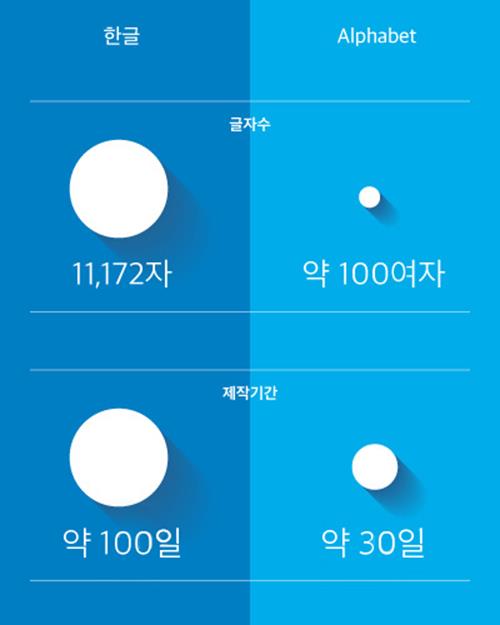
한글 폰트를 만드는데 이렇게 많은 비용이 필요하다 보니, 많은 수의 소규모 한글 폰트 업체들은 좋은 한글 폰트를 만드는 능력을 키우기보다는 쉽게 빨리 만들어서 모바일 플랫폼에 판매함으로써 생계를 유지하고 있습니다. 심지어 몇몇 업체에서는 유명한 폰트나 디자인 작품을 표절해서 한글 폰트를 만들기도 하고, 이렇게 표절한 폰트들이 방송과 광고 등에 부끄럼 없이 사용되는 일도 자주 벌어지고 있습니다. 안타까운 현실이지만 이들에게는 생계가 달려 있는 문제이기 때문에 무조건 탓할 수도 없습니다.
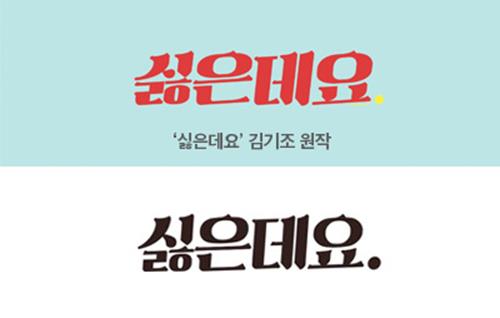
그리고 많은 분들이 가장 크게 오해하고 있는 부분이 한글 폰트 회사들이 저작권 단속을 통해 많은 돈을 벌고 있다고 생각하는 것입니다. 우리나라에서 가장 큰 한글 폰트 회사인 산돌과 윤디자인, 두 회사의 1년 매출을 합해도 80억원 정도에 불과하고 순수익은 별로 없는 것이 현실입니다. 규모가 작은 회사들은 더욱 심각한 상황입니다. 한글 폰트 디자이너들이 좋은 폰트를 만들기 위해 많은 야근을 하면서도 박봉에 시달리는 이유가 달리 있지 않습니다. 우리나라에서 한글 폰트 회사들은 많은 돈을 벌기는 고사하고, 늘 생존의 위협을 받고 있습니다. 폰트 업계가 저작권 단속에 매달리는 이유가 여기에 있습니다.
한글 폰트 저작권 단속의 실체
한글 폰트 업체들의 폰트 저작권 단속이 비난 받는 이유는 ‘함정 단속’ 때문입니다. ‘개인적 용도에는 무료’라고 배포해 놓고, 라이선스 범위에 대해서는 모호하게 감춘 다음 함정에 걸리면 ‘상업적인 용도’에 사용했다면서 단속을 해서 비싼 합의금을 요구하는 방식입니다. 이런 방법이 효과를 거두자 더 대담하게 네이버 등의 포털 서비스를 통해서 무료 폰트라며 대량 배포해서 더 많은 피해자를 양산하는 사태에 이르고 있습니다. 이 회사들이 함정 단속을 하는 이유는 이들의 폰트를 돈을 내고 구매하는 사람이 없기 때문에, 단속을 마치 영업 활동처럼 여기기 때문입니다. 값을 지불하기에는 폰트 품질이 부족하다는 것이 가장 중요한 이유겠지만, 그만큼 폰트를 제 값 주고 구매하는 사람이 별로 없다는 것도 사실입니다. 앞으로도 이 회사들의 한글 폰트를 사용할 생각이라면 무료 폰트라는 말에 속지 말고, 라이선스에 대해서 정확히 확인한 후에 사용하는 것 밖에는 방법이 없습니다. 함정이라는 것을 정확히 알고, 함정을 피해야 합니다.
한글 폰트는 그냥 써도 저작권 침해가 아니라는데요
‘폰트는 저작권이 없다, 그러니까 그냥 써도 된다’
이 이야기가 마치 사실인 것처럼 통용되고 있습니다. 이런 큰 오해가 발생하게 된 것은 정부와 기관의 탓이 크지만, 단속에만 열을 올리고 고객들과 소통에는 소홀했던 한글 폰트 업체들에게도 책임이 있습니다. 너무도 당연한 이야기지만 폰트도 저작권법 상의 프로그램 저작물로 보호되고 있습니다. 따라서 저작권자의 허락 없이 폰트를 사용하게 되면 저작권 침해에 해당합니다.
그러면 왜 폰트는 저작권이 없다는 얘기가 나온 것일까요? 한글 폰트에 대해 저작물로 인정되지 않는 부분이 한가지 있는데 그것이 한글 폰트의 도안 즉 ‘디자인’ 입니다. 폰트의 핵심이 서로 다른 폰트임을 구분할 수 있는 ‘디자인’ 임에도 불구하고, 저작권 법에서는 고딕체와 명조체를 서로 같은 디자인이라고 판단하고 있는 것입니다. 여러분이 생각하기에도 고딕체와 명조체는 같은 것으로 생각되시나요?
한글 폰트의 디자인을 저작물로 인정하지 않는 이유는, 모든 한글 폰트가 세종대왕 시절에 고안된 한글을 똑같이 그리고 있는 것 뿐이기 때문에 새로운 창작물로 볼 수 없다는 것입니다. 김수현을 사진으로 찍으면 그 사진들은 모두 각각의 저작물로써 촬영자에게 저작권이 발생하게 되고, 김수현은 별도의 초상권을 행사하게 됩니다. 그런데 한글 폰트는 오랜 시간을 들여서 디자이너의 창작 활동을 통해 각기 다른 모양으로 그려내도 저작물로 인정해주지 않는다는 것이 현재 한글 폰트에 대한 제도적 인식입니다. 왜 김수현의 똑같은 모습을 찍은 사진에는 저작권을 인정해주고, 한글은 인정해주지 않는 걸까요?
폰트의 디자인을 저작물로 인정하지 않는 저작권법의 해석 때문에 ‘폰트는 저작권이 없다’라는 큰 오해가 발생한 것입니다. 심지어 똑같은 폰트의 디자인을 복사해서 새로운 폰트라고 이름 붙여도 법률상으로는 아무런 문제가 없습니다. 어도비나 모노타입과 같은 거대 기업이 한국에 있는 모든 한글 폰트를 그대로 표절해서 새로 이름을 붙이고, 자기들의 폰트라고 주장해도 우리나라의 저작권법으로는 대응할 방법이 없습니다.
‘폰트 디자인도 디자인보호법으로 보호됩니다’
저작권법이 폰트의 디자인은 저작물로 보호하지 않으니까 폰트 디자인은 마음대로 베껴서 사용해도 된다고 생각할 수 있습니다. 실제로 폰트 저작권 단속에 걸린 사람들이 주장하는 것이 ‘폰트 파일을 사용하지 않았고, 폰트 디자인만 따서 사용했다’라는 것입니다. 하지만 폰트의 디자인만 도용한 것도 처벌받을 수 있다는 사실은 제대로 알려지지 않았습니다.
저작권법은 폰트 파일만 보호하고 폰트 디자인은 보호하지 않지만, 별도의 법률인 디자인보호법에서는 폰트의 디자인까지 온전히 보호하고 있습니다. 그러니까 폰트의 디자인은 저작권 침해가 아니라고 생각해서 무심코 사용했다가 디자인 등록이 돼 있는 폰트라면 디자인보호법 위반으로 처벌될 수 있습니다.
● 폰트는 저작권법 상에 프로그램 저작물로 보호됨
→ 따라서 저작권자의 허락 없이 폰트 파일을 이용하거나 복제, 전송하는 것은 저작권 침해
● 폰트 디자인은 디자인보호법으로 보호됨
→ 따라서 폰트 파일을 사용하지 않았더라도, 디자인 등록된 폰트의 디자인을 도용하면 디자인보호법 위반
디자인보호법이 있다면 굳이 폰트 디자인에 대해 저작권을 인정해달라고 할 필요가 없지 않느냐는 얘기도 많이 듣습니다. 반대로 디자인보호법에서 폰트 디자인 보호하고 있다는 것은 폰트 디자인을 보호할 필요성을 제도적으로도 이미 인정하고 있다는 의미인데, 저작권법에 포함하면 간단할 일을 별도의 등록 절차와 비용이 필요하고, 국제적으로는 인정되지 않는 디자인보호법에서 다루는 것은 행정력과 비용 낭비일 것입니다.
‘폰트의 글자 디자인은 사용했는데, 폰트 파일은 쓰지 않았다구요?’
폰트를 사용한 결과물은 있는데, 폰트 저작권을 침해하지 않았다는 주장은 ‘폰트를 사용하지 않고 똑같은 글자 모양을 만들어냈다’는 얘기가 됩니다. 정말 폰트 파일을 사용하지 않고도 그런 작업을 할 수 있을까요? 밥은 먹었는데 쌀은 먹지 않았다고 주장할 수 있을까요?
이런 행위를 합리화시키기 위해서 ‘한글 폰트에는 저작권에 없다’라고 당당하게 주장하고, 정당한 라이선스 없이 폰트 파일을 사용한 것까지 무고하다고 주장하는 것은, 저작권법과 디자인보호법을 거론하기 이전에 스스로의 양심과 정의에 반하는 행동일 것입니다. 자신의 저작물이 소중한 만큼만 한글 폰트의 저작권도 인정해주면 분쟁의 소지도 없을 것입니다.
‘한글 폰트 저작권에 대해서 바로 알아주세요’
폰트의 디자인을 창작된 저작물로 인정하고, 디자인보호법이 아닌 저작권법으로 보호하는 제도적 보완은 오랜 시간이 필요할 것입니다. 하지만 더 이상 한글 폰트는 아예 저작권이 없다는 오해는 사라져야겠습니다. 폰트 파일 없이 폰트의 디자인만 사용했다는 억지도 더 이상 없어야겠습니다. 한글 폰트에 대한 창작을 인정해 줄 때 폰트 디자이너들이 더 좋은 한글 폰트를 만들어내려는 노력이 커질 것이고, 외국 기업들의 한글 폰트 표절도 예방할 수 있을 것입니다.
그렇다고 모든 폰트가 11,172자를 만드는 것도 아니고…
대다수의 폰트는 2,350자만 만드는데 이 글은 약간 과장이 들어간 것 같습니다